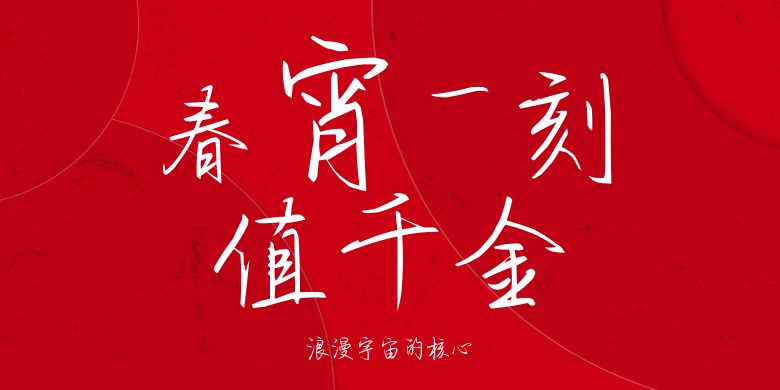
浪漫宇宙的核心
浪漫宇宙的核心,这款字体结构工整、笔画清晰,兼顾美观与易读性,适用于标题、正文、海报、包装、LOGO 等多种场景。字形优雅稳定,风格百搭耐看,适配日常排版与创意设计,让文字呈现更舒适、更具质感。浪漫宇宙的核心一笔一画,皆是细节,以均衡的比例、流畅的线条打造舒适视觉体验,字形端正大气,风格简约现代。无论是商业设计、品牌宣传还是日常排版,都能轻松驾驭,让文字更有格调与力量。浪漫宇宙的核心字体下载。